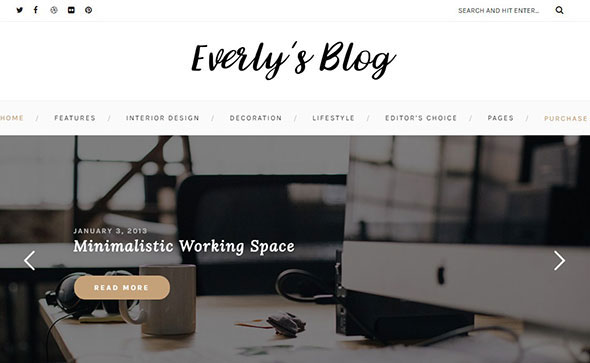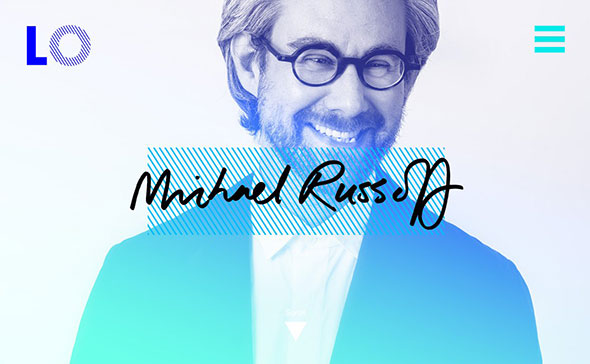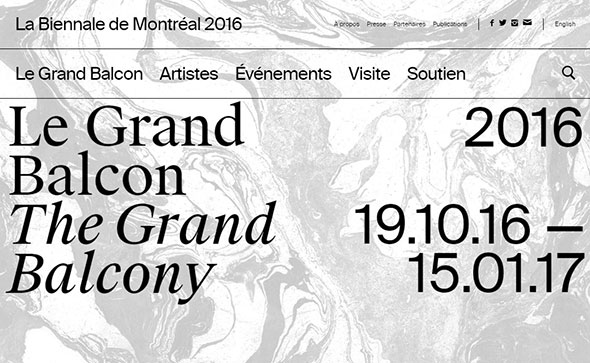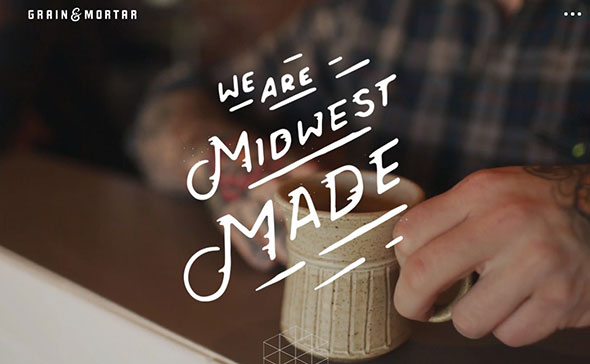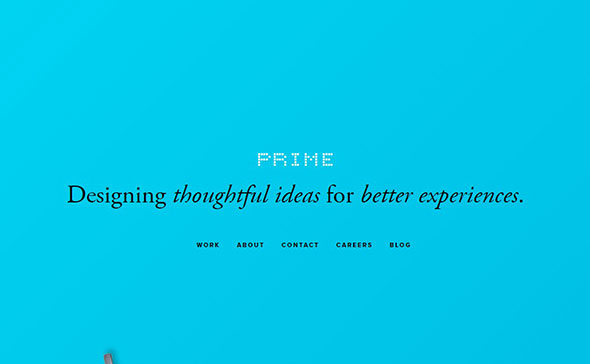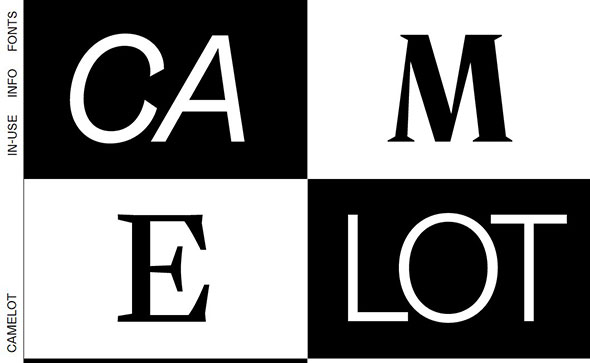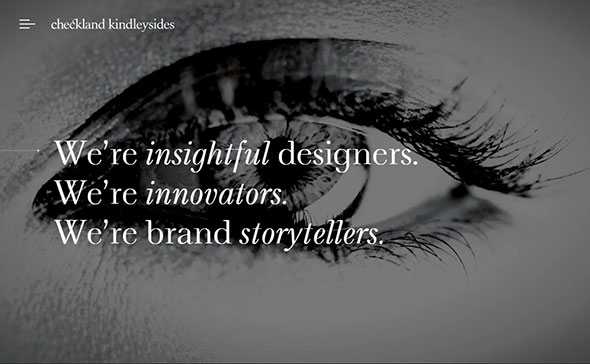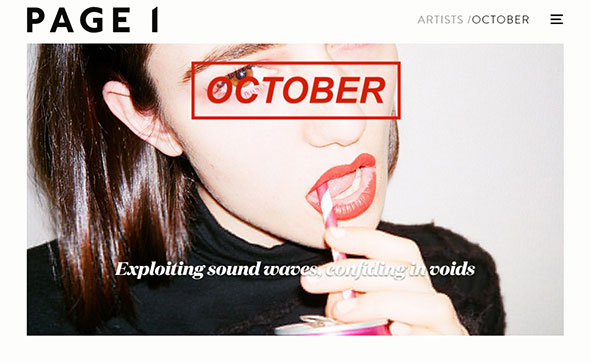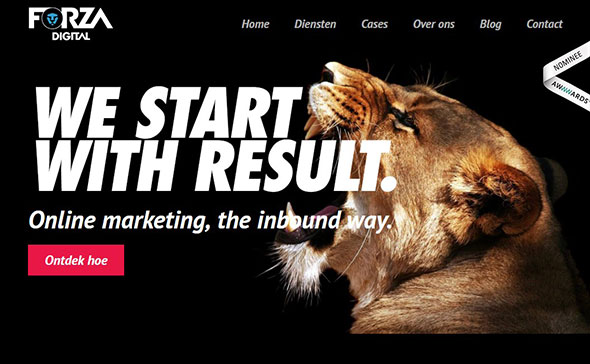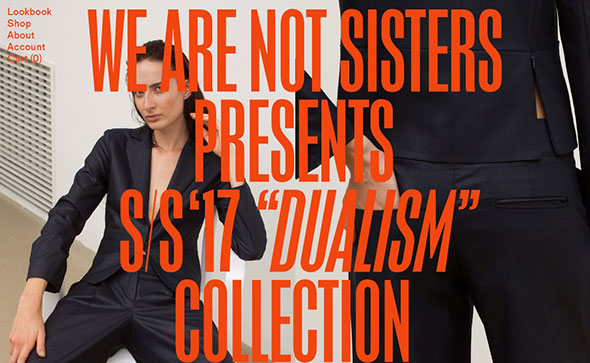
Курсивные шрифты в веб-дизайне
Курсивные шрифты в этом году будут в тренде. В веб-дизайне это отличный способ выделить ту или иную информацию. Также курсив поможет создать легкую, игривую, романтичную атмосферу. Сегодня мы собрали сайты, на которых использован курсивный шрифт.